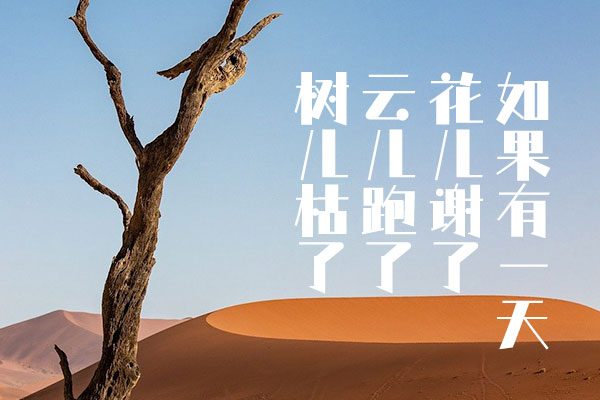
仓耳非白
仓耳非白字体是仓耳字库推出的一款免费字体,拥有强烈的风格和5种字重,结构规整、简洁、利落。在设计中,我们强调“黑”的粗犷感和“白”的细腻感,使字体在粗细对比中呈现出独特的风格。
字体设计简洁大方,转折处采用直角处理,撇捺以直线表现,形成了鲜明的视觉效果。同时,我们将点的部分改为圆形,使字体看起来更加柔和。
仓耳非白效果预览